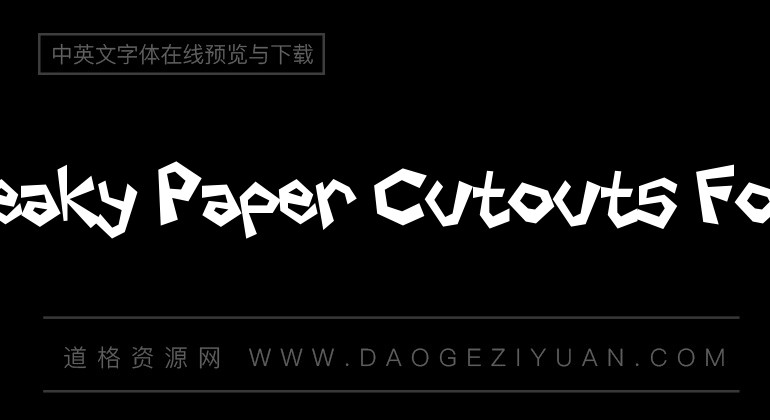
Freaky Paper Cutouts是一款独特的字体,由设计师 Oliver Pflug 捏造并发布于 MyFonts 网站上。这种字体的设计灵感来自于手工剪纸艺术和印刷术。 Freaky Paper Cutouts 字体的特点是字母的线条非常粗糙,仿佛是用手工剪纸技艺剪出来的一样。整体感觉非常有趣和怪异,适合用于标题、广告或海报等设计用途。 该字体提供了多种字重和字形,包括正常、粗体和斜体,支持多种字符集和语言。Freaky Paper Cutouts 字体的许可证允许个人和商业用途,可以在 MyFonts 网站上购买。内容介绍
Freaky Paper Cutouts Font是一款非常不错的手写艺术字体,具有很好的视觉感,适合于文化类的宣传设计、商业类品牌的广告和产品包装设计以及个性化文字排版等较多场景。